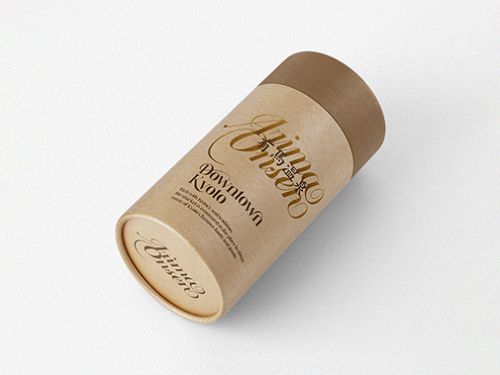
Daizen
【Daizen:优雅手写风免费商用英文字体】 Daizen是一款极具设计感的英文手写体字体,隶属于Handwriting分类,以温和亲切的手写风格与端庄优雅的视觉气质著称。作为免费商用英文字体,Daizen采用修长的字形设计,配合居中的重心与适中的中宫结构,既保证了文字的优雅舒展,又带来稳定舒适的阅读体验。 Daizen的笔型设计富有巧思,独特的斜切处理与方头笔画形成鲜明记忆点,粗体字重配合均匀的笔画分布,使字体在保持手写灵动性的同时兼具现代设计感。 Daizen的笔画连接方式为断开设计,既保留手写体的自然韵律,又确保文字识别度。无论是品牌标题设计、广告宣传物料还是社交媒体配图,Daizen都能以其独特的粗体手写风格传递温暖亲切的情感,是设计师提升作品质感的理想选择。